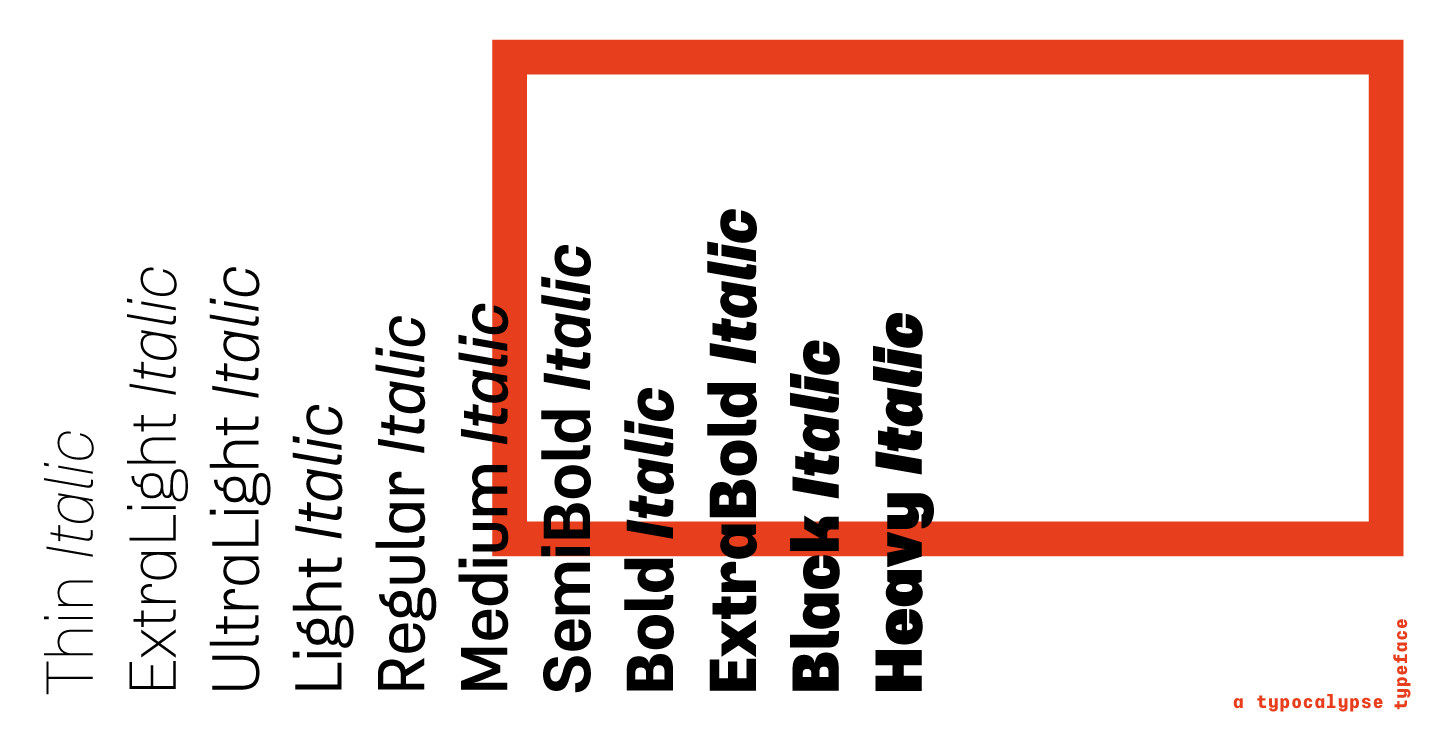
Vintage-Grotesk von Typocalypse
Mit »Typewalk 1915« präsentiert Typocalypse eine neue Vintage-Grotesk-Schriftfamilie. Die Fonts stellt eine Hommage an die europäischen Schriftenmaler und Lettering-Tradition des frühen 20. Jahrhunderts dar.
»Typewalk 1915« bietet elf unterschiedliche Schriftgewichte inkl. passender kursiver Schnitte. Ergänzend dazu gibt es die Monospaced-Variante »Typewalk Mono 1915«. Die von Sven Fuchs gestalteten Fonts eignen sich somit zum Beispiel für Anwendungen in den Bereichen Kultur, Editorial und Branding.